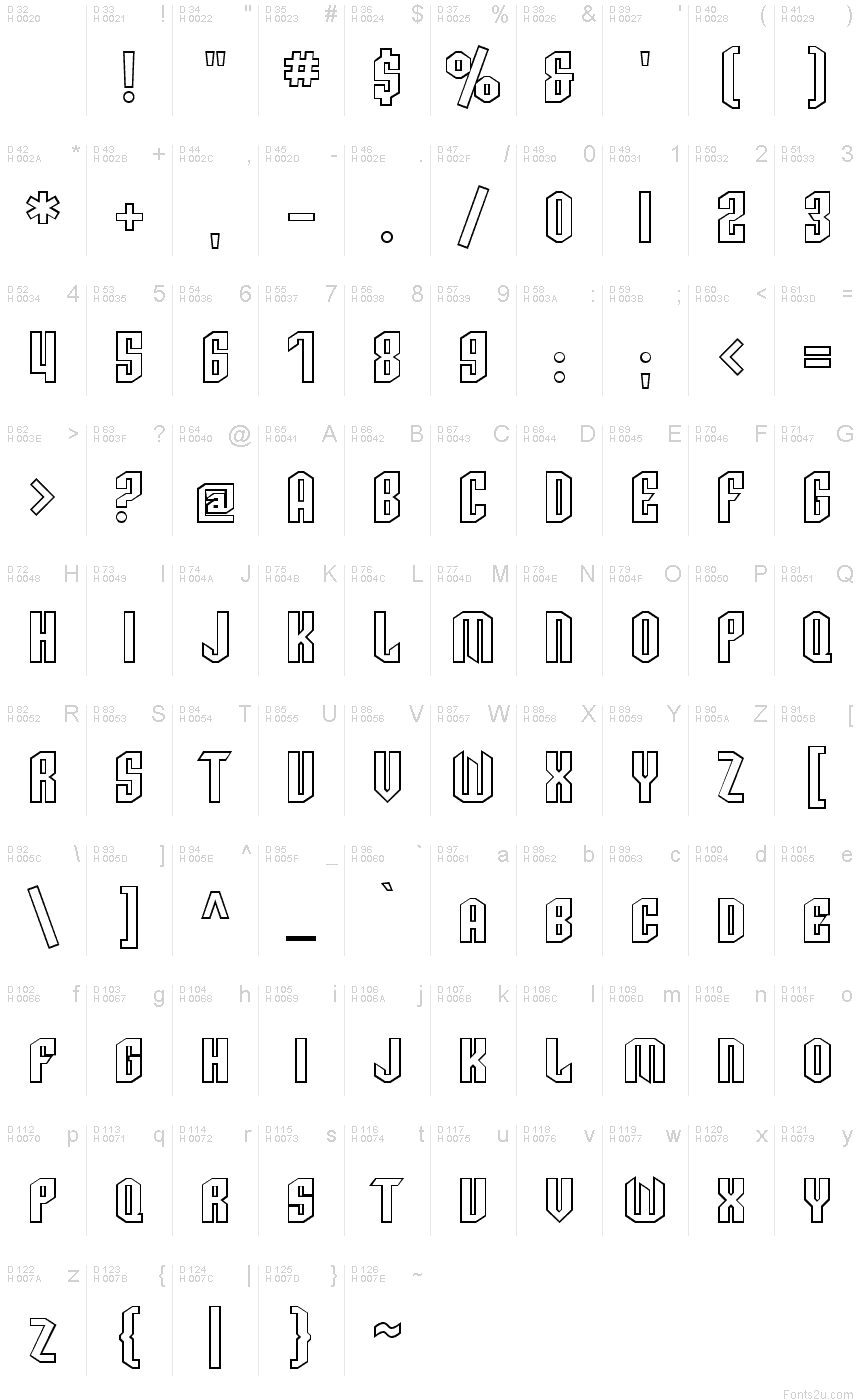
SF Archery Black SC Outline
SF Archery Black SC Outline di ShyFoundry è un font display techno gratuito con contorno e un'attitudine cruda, tipica dell'era arcade. Le maiuscole sono costruite con linee quadrate, ottagonali e tagli profondi; l'alfabeto ricorda uno stencil inciso su vecchio hardware da gioco o su loghi sportivi ridotti all'essenziale.
È perfetta per titoli di poster, branding e-sport, copertine di mixtape, titoli video e monogrammi che richiedono un font gratuito dal carattere rigido e meccanico, piuttosto che uno stile futuristico levigato. Grazie alle lettere ampie, massicce e aperte al centro, questo font dà il meglio di sé in parole brevi e iniziali, lasciando che sia la silhouette angolare a definire lo stile.